우아하고 세련된 폰트를 찾는다면? 산돌구름이 추천하는 패션 매거진들의 최애 폰트 4종
고급스러운 무드를 완성해 주는 라틴 세리프 폰트
패션 매거진이나 럭셔리 브랜드 로고에서 자주 보이는, 우아하고 세련된 인상의 폰트들이 있습니다.보그(VOGUE)의 제호, 자라(ZARA)의 로고에 쓰인 디도(Didot)와 보도니(Bodoni)가 대표적인 예로, 디돈(Didone) 양식이라는 이름으로 불리는 세리프 스타일의 폰트들이죠. 산돌구름이 이들 스타일을 기반으로 한, 감각적인 라틴 세리프 폰트들을 소개해 드리도록 하겠습니다.
1.프로덕션타입 / Trianon Display
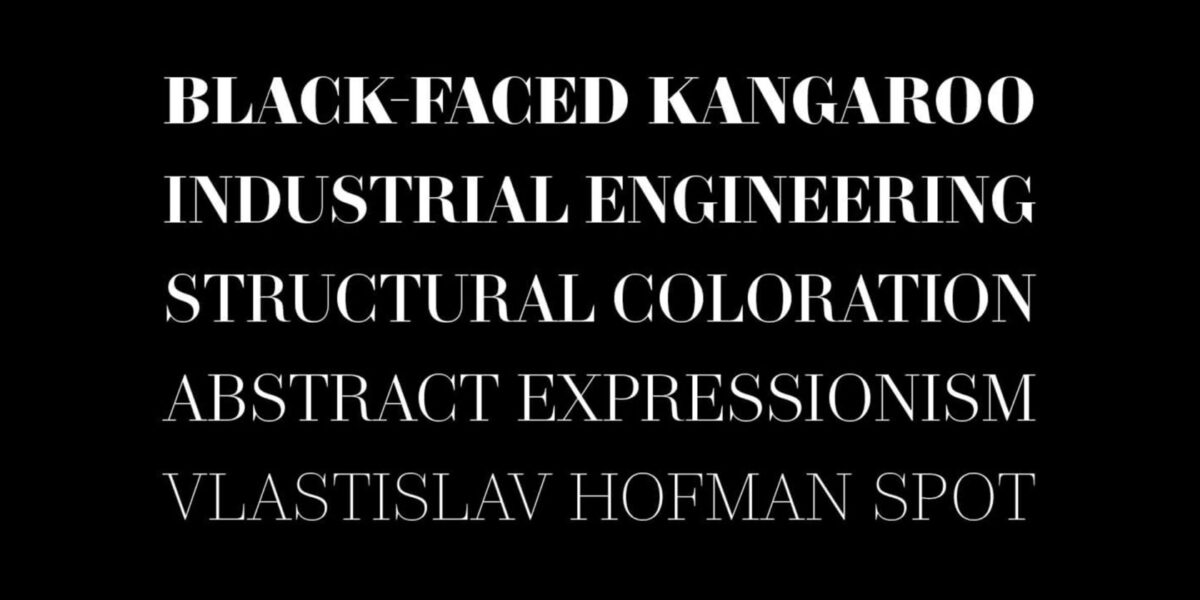
‘Trianon Display’는 프랑스 파운더리인 프로덕션타입(Production Type)에서 제작한 폰트입니다. 디도를 디자인한 Firmin Didot의 후기 작업과 19세기 말부터 20세기 초까지 프랑스에서 만들어진 서체들을 직접 참고하고 연구해, 현대적인 감각으로 재해석한 폰트인데요. 깔끔하게 정제된 구조, 리듬과 가독성 등이 돋보이는 퀄리티 높은 폰트입니다.
2. 플레이타입 /Italian Plate No4 Display
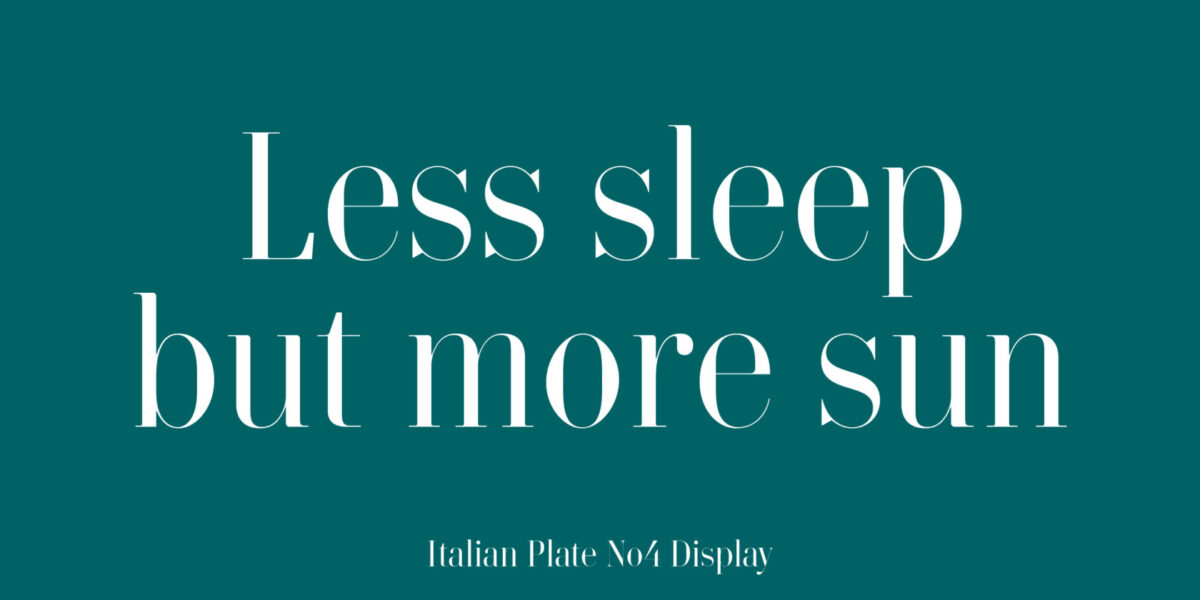
플레이타입의 인기 폰트 중 하나인 「Italian Plate No4」 는 살짝 좁은 비율에 타원형 리듬이 살아 있는 구조로 디자인된 폰트입니다. 얇은 획과 굵은 획의 극적인 대비가 특징으로, 마치 스틸레토 힐처럼 우아하고 날렵한 인상을 주죠. 세모꼴의 세리프나, 은은하게 라운드 처리된 모서리 등, 곳곳에 섬세한 디테일이 숨어 있어 보는 재미도 있습니다. 특히 이탤릭 스타일은 로마체와는 다른 감성으로 유려한 흐름과 세련된 분위기를 전달합니다. 코스메틱 패키징에나 로고에도 잘 어울릴 것 같은 인상입니다.
3. 제타폰트 / Lovelace Display
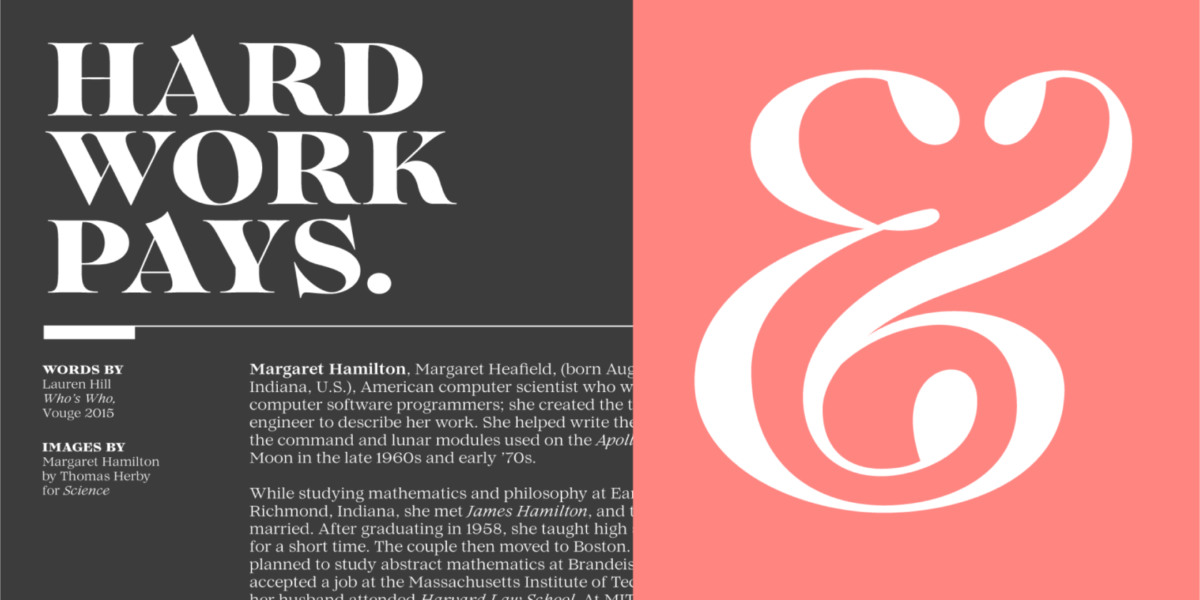
제타폰트의 「Lovelace Display」는 이름에 들어간 “러브”처럼, 로맨틱한 무드가 자연스럽게 전달되는 폰트입니다. 세리프의 형태가 직선으로 딱 끊기는 대신 기둥과 부드럽게 이어지도록 설계되어, 전체적으로 유려하고 섬세한 인상을 주죠. 화려한 화보의 타이틀, 또는 몇 글자만으로 집중을 끌어야 하는 시각적 포인트를 만들고 싶을 때, 예시 이미지처럼 대문자만으로 조판해 써보는 것은 어떨까요?
4. 로제타타입 / Butik
로제타타입의 ‘Butik’은 무려 28종의 웨이트로 구성되어 있어, 굵기와 너비의 선택지가 정말 다양한 폰트입니다. 디돈 스타일의 계열에 속하면서도, 어딘가 인상이 더 통통 튀고 발랄한 느낌을 주는데요.
소문자 r, a, c 등에 들어간 획 끝처리 장식인 동그란 물방울 모양의 볼 터미널(ball terminal)과, 반복되는 곡선 표현에서 비롯되죠. 사랑스러우면서도 장난기 가득한 감성이 묻어나는 컬러풀한 이미지와 함께하면 특히 잘 어울릴 것 같아요. 얇고 굵은 획의 차이가 커 큰 사이즈에서 사용하는 것을 추천드립니다.